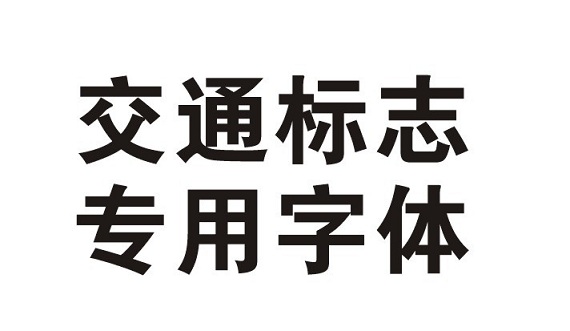
交通標(biāo)志專(zhuān)用字體是一款道路交通標(biāo)志專(zhuān)用字體,交通標(biāo)志主要為符號(hào)和文字類(lèi),而大家在公路上常見(jiàn)的標(biāo)識(shí)語(yǔ)前方左轉(zhuǎn)、路滑慢行、陡坡慢行等都是用專(zhuān)業(yè)的交通標(biāo)志字體設(shè)計(jì)的,需要這樣的字體素材的朋友趕緊下載吧。
交通標(biāo)志,用文字或符號(hào)傳遞引導(dǎo)、限制、警告或指示信息的道路設(shè)施。又稱(chēng)道路標(biāo)志、道路交通標(biāo)志。在交通標(biāo)志中一般是以安全、設(shè)置醒目、清晰、明亮的交通標(biāo)志是實(shí)施交通管理,保證道路交通安全、順暢的重要措施。 交通標(biāo)志有多種類(lèi)型,可用各種方式區(qū)分為:主要標(biāo)志和輔助標(biāo)志;可動(dòng)式標(biāo)志和固定式標(biāo)志;照明標(biāo)志、發(fā)光標(biāo)志和反光標(biāo)志;以及反映行車(chē)環(huán)境變化的可變信息標(biāo)志。